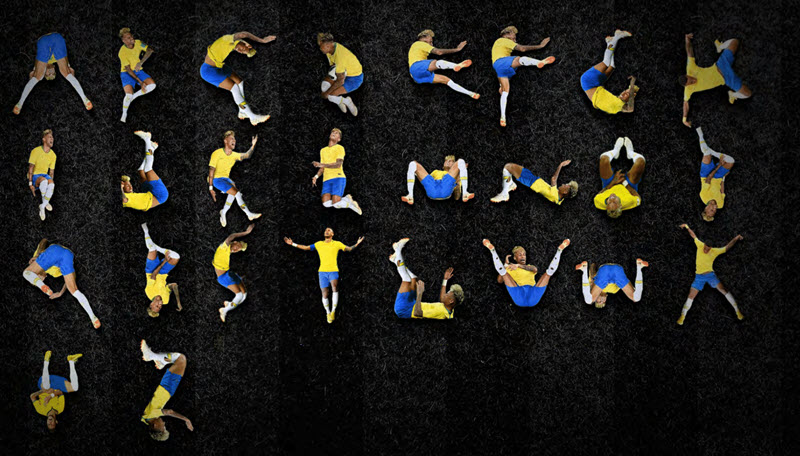
انتقاد و شوخی با نیمار به خاطر عملکرد بدش در جام جهانی با طرح حروف یا تایپفیس او به اوج رسید!
با آغاز جام جهانی همه میدانستیم که عملکرد نیمار زیر ذرهبین خواهد بود. در جام جهانی قبلی، نبود او در فاجعه شکست 7 به یک برابر آلمان، توجیهی بود بر غم برزیلیهای عاشق فوتبال.
اما در جام جهانی روسیه هم خیلیها منتظر بودند که از او انتقاد کنند و بعد بگویند که نیمار آن طورها که تبلغش را میکنند، نمیتواند بازیکن تأثیرگذار میدانهای بزرگ باشد.
اغراق او بعد از یکی از خطاهایی که روی او انجام شد، زمینهساز یکی از شوخیها با او شد و گیفها و ویدئوهایی از او ساخته شد که در آن وی را در حال غلت زدنهای بیپایانی که از زمین چمن شروع میشد و به خیابانهای اطراف میانجامید، میدیدیم.
در این میان اریک کانتونا هم در ویدئوهای کوتاهی عملکرد و ظاهر نیمار را به تمسخر گرفته بود. مثلا در ویدئوی اول ظاهر موی نیمار، مورد توجه کانتونا قرار گرفته بود.
اما در اقدام جالبی فیگورهای نیمار در بازیهای جام جهانی روسیه، الهامبخش تهیه یک تایپفیس شده است که شما میتوانید با مراجعه به اینجا آن را در فرمتهای مختلف دانلود کنید!